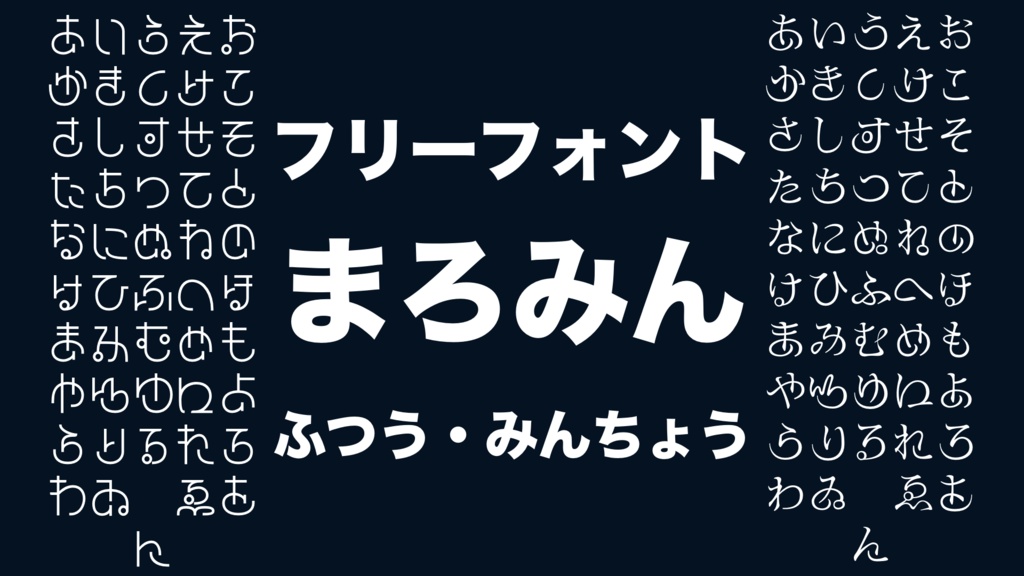
まろみん - 個性派ひらがなフリーフォント
新作フリーフォント「異端仮名『怪』」登場!ぜひご利用ください! https://fontring.booth.pm/items/3213962 ひらがなのフリーフォント「まろみん」 です。線を省略したり断絶させたり、円形部分を独立させるなどの操作によって美しいまろみを実現したデザインフォントとなっています。 「ふつう」「みんちょう」の2スタイルを同梱しています。「みんちょう」は明朝体用のひらがな風になるように「ふつう」を改造したものです。 無連絡での商用利用可能です。 【重要】投げ銭用のバージョンは無料のバージョンと全く同一のものが入っています。 投げ銭を検討される方は、下記のフォントをご購入くださいますことも大変励みになります。 ・欧文/カタカナフォント CORORIN https://fontring.booth.pm/items/871969 ・欧文フォント Lemonin https://fontring.booth.pm/items/1156944 作ったフォントが使われているのを見るのが好きです。作品を投稿する際にタグ「#まろみんフォント」をつけたりクレジットに記載したりしていただくと見つけやすいので嬉しいです😉 このフォントを紹介される際、Boothのサンプル画像は自由にご利用ください。 フォントのバージョンアップのお知らせはこちらで投稿します。フォローお願いします🙏 https://www.pixiv.net/fanbox/creator/31276656